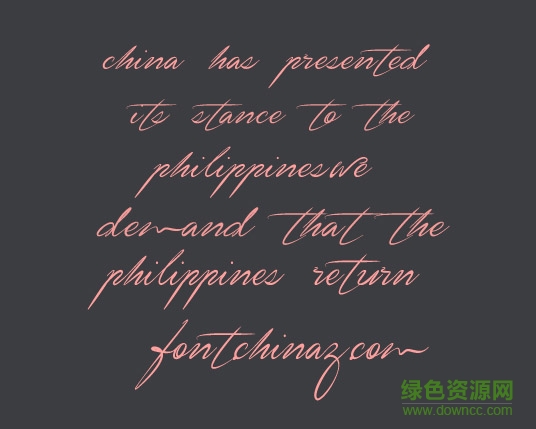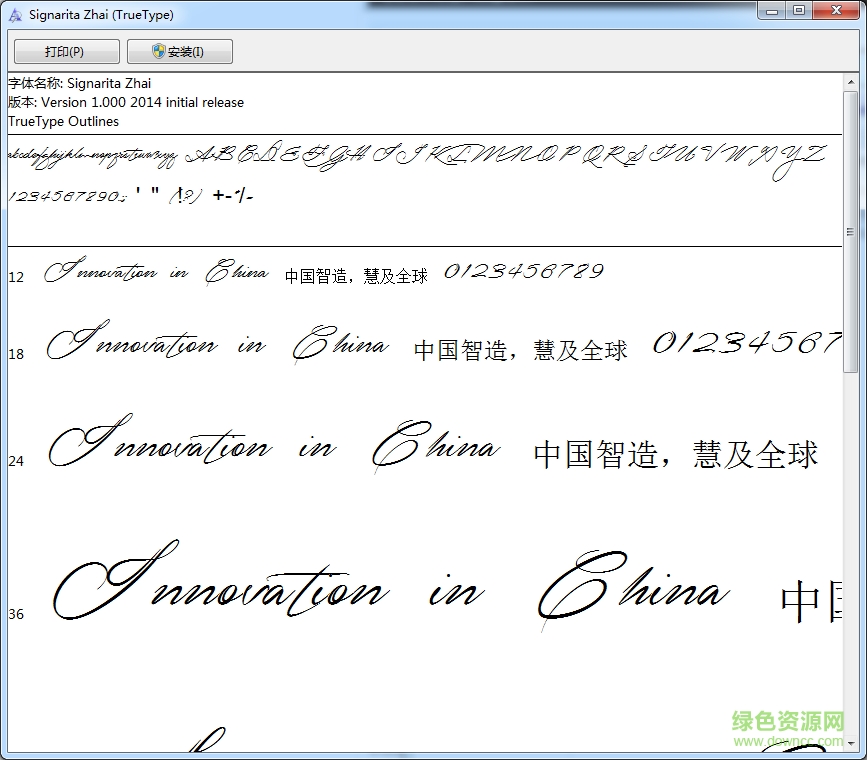
Signarita Zhai字體
Signarita Zhai字體是一款別具一格的電腦字體軟件,支持英文中文漢字等多種輸入,字體傾斜有致使用簡單,常用于多種行業(yè)領(lǐng)域??靵砭G色資源網(wǎng)下載體驗吧!
Signarita Zhai字體介紹
Signarita Zhai字體是一款非常有特色的藝術(shù)字體,這款字體風(fēng)格簡約,字體字形圓潤,能夠運用到藝術(shù)創(chuàng)作以及影視。
Signarita Zhai字體